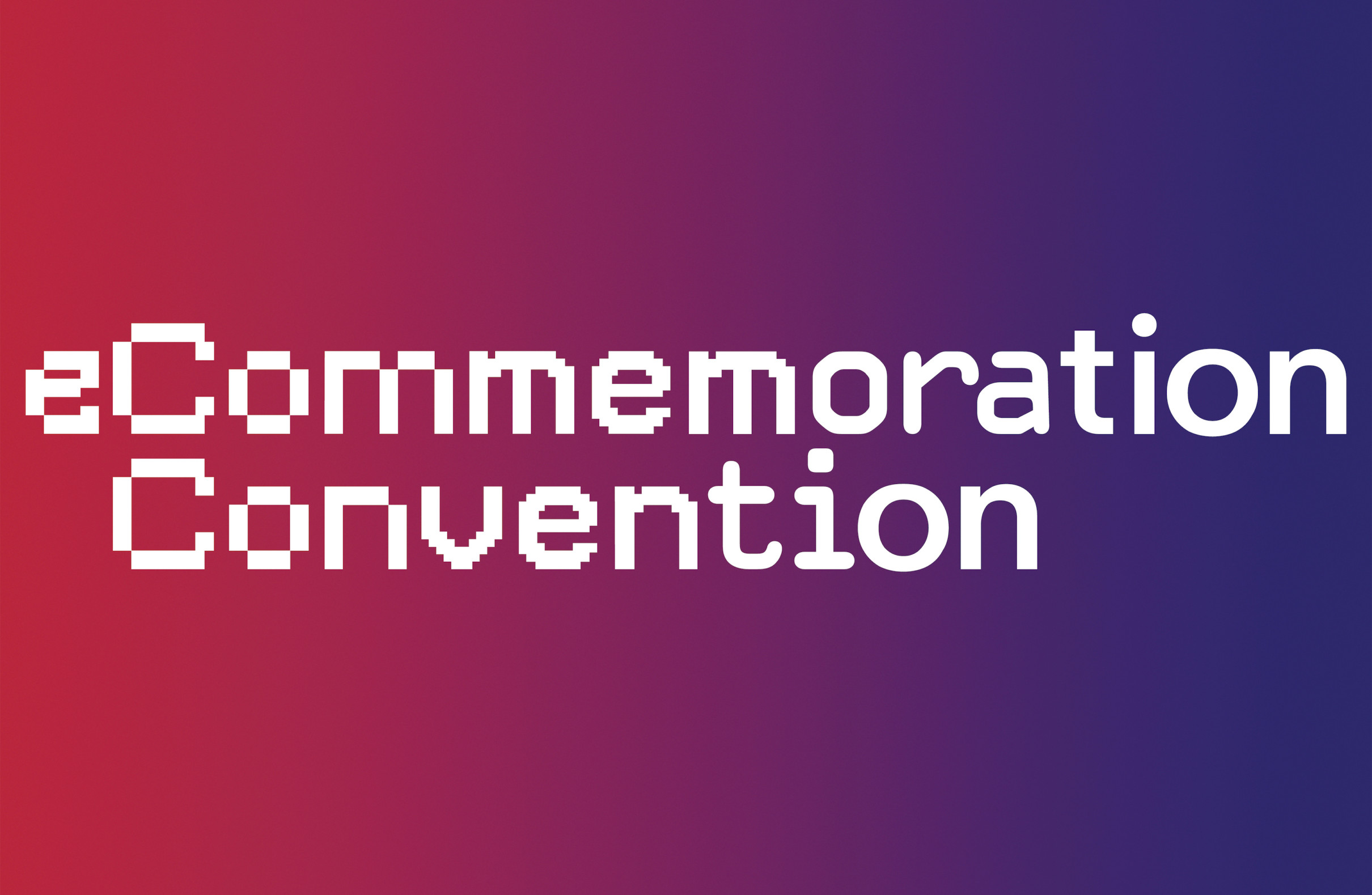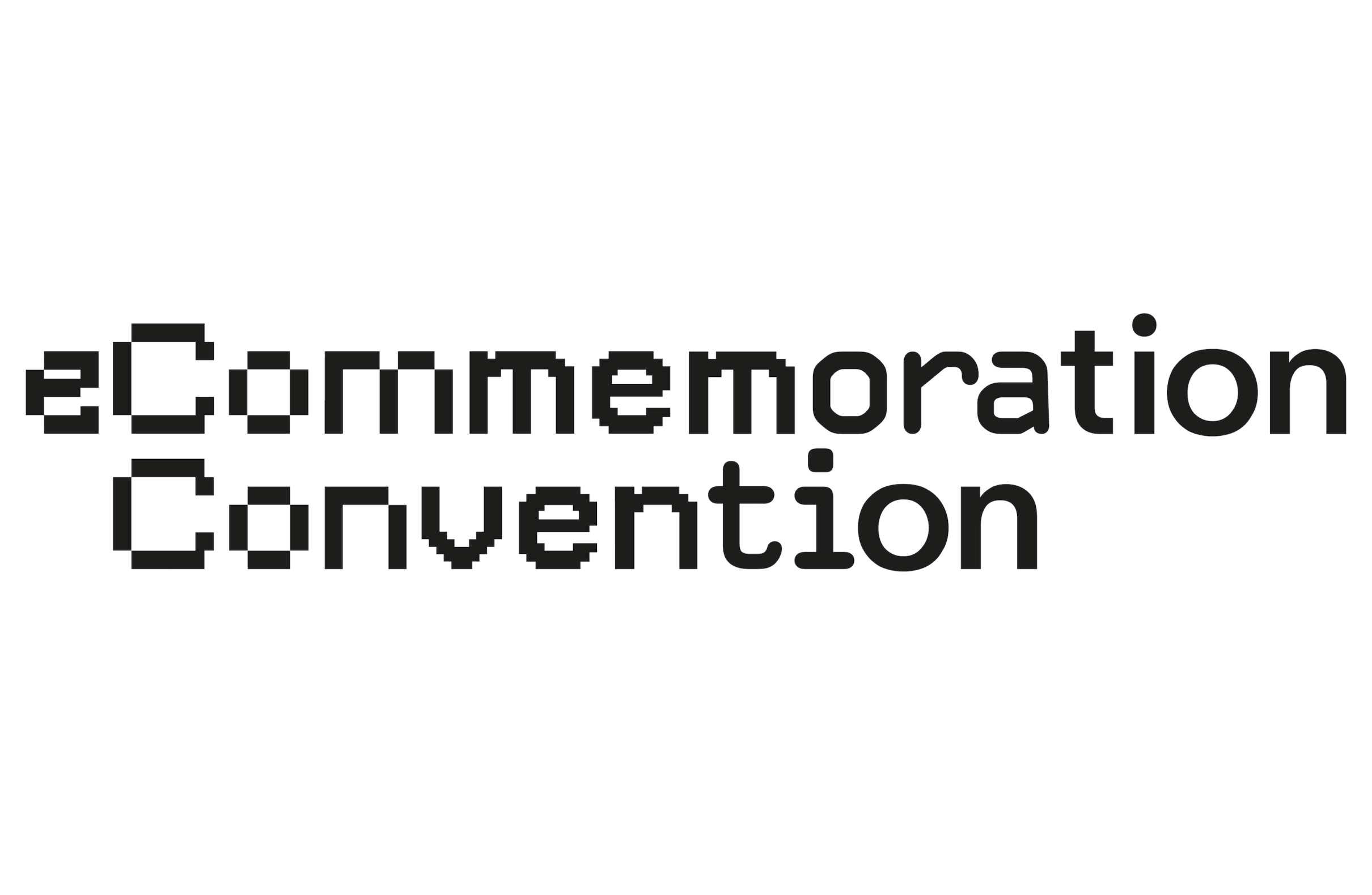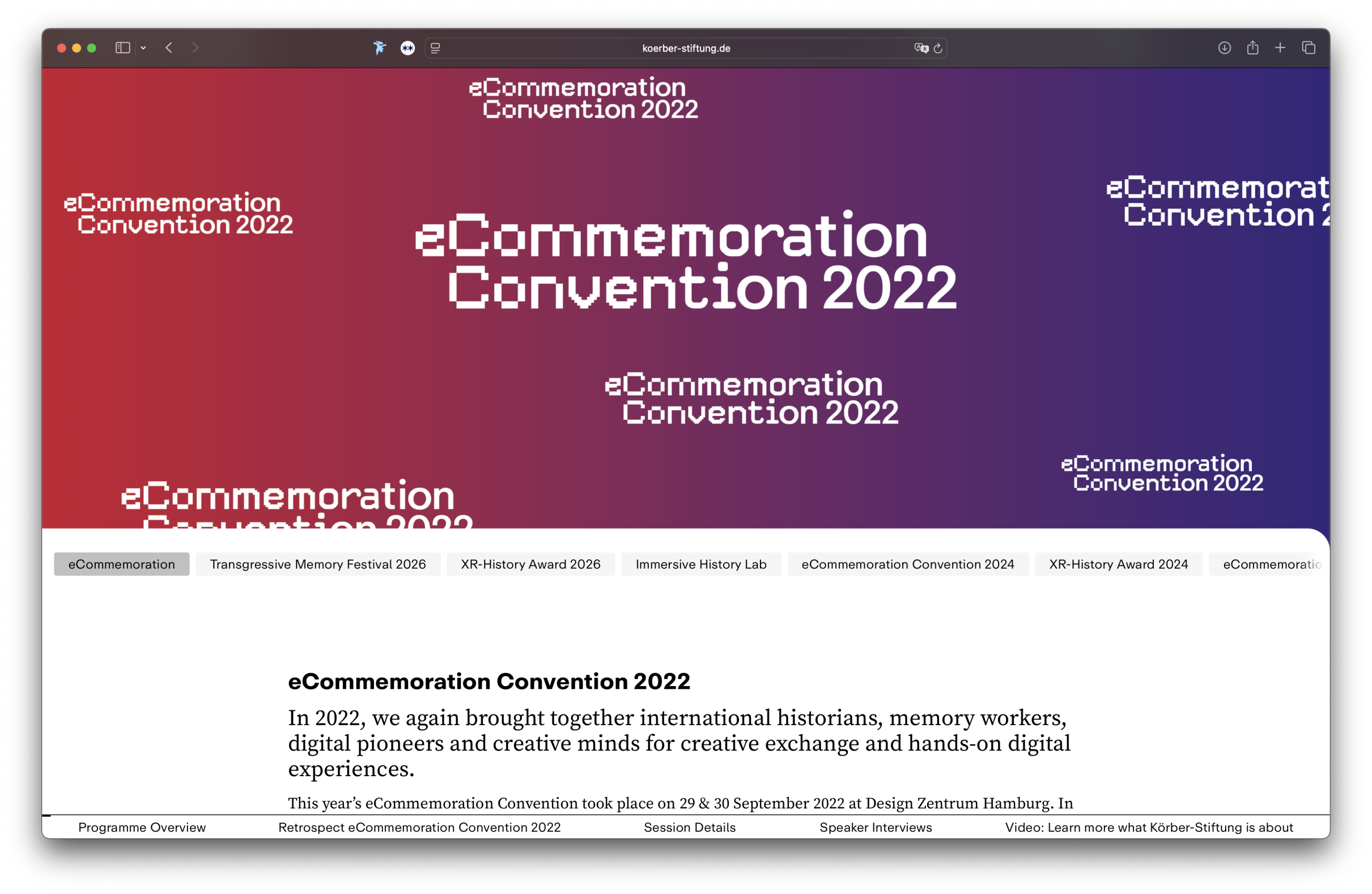
eCommemoration Convention
Logogestaltung für die eCommemoration Convention der Körber Stiftung Hamburg.
Die eCommemoration Convention fand am 29. und 30. September 2022 im Design Zentrum Hamburg statt. In verschiedenen Panels diskutierten internationale Teilnehmer mit unterschiedlichen Perspektiven, Hintergründen und Berufen darüber, wie die Digitalisierung die Geschichte neu definiert. Abgerundet wurde die zweitägige Veranstaltung durch Workshop-Formate, in denen die Teilnehmer*innen praktische Erfahrungen sammeln konnten.
Das Logo entwickelt sich von einer verpixelten Schrift hin zu einer klaren, gradlinigen Groteskschrift und spielt damit auf die Entwicklung digitaler Darstellungsformen an.
Schriften: Minecraft, VCR OSD Mono, OCR B & Körber Repro